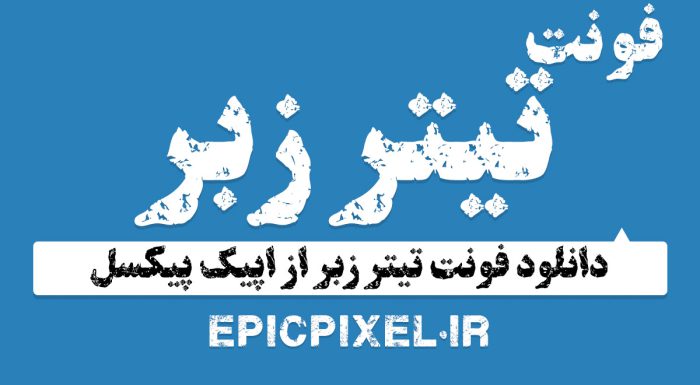
فونت تیتر زبر فارسی
| ⭐ توضیحات | زیر مجموعه از فونت تیتر |
فونت تیتر زبر چگونه از یک فونت ساده یک فونت گرافیکی خلق کنید؟
فکر میکنید برای داشتن یک فونت گرافیکی زیبا و خاص، باید حتما یک طراح حرفهای باشید؟ اگر جوابتان بله است، شاید بعد از خواندن این مقاله نظرتان عوض شود. در این مقاله قصد داریم با شما درباره فونت تیتر زبر صحبت کنیم. یک فونت گرافیکی افکتیو که با تغییر شکل و ایجاد بافت بر فونت تیتر بدست آمده است. این فونت را ملیحه نوازشپور، یک دانشجوی طراحی گرافیک، در قالب یک پروژه دانشجویی خود در کارگاه مسلم ابراهیمی، یک طراح و مدرس فونت، انجام داده است. در این مقاله به شما معرفی میکنیم که فونت تیتر زبر چیست؟ چه ویژگیها و کاربردهایی دارد؟ چگونه میتوانید آن را دانلود و نصب کنید؟ و چگونه از آن در طراحی لوگو و بنر استفاده کنید؟ همچنین نظرات کاربران را درباره این فونت با شما به اشتراک میگذاریم. پس با ما همراه باشید.
فونت تیتر زبر چیست؟
فونت تیتر زبر یک فونت گرافیکی افکتیو است که با تغییر شکل و ایجاد بافت بر فونت تیتر بدست آمده است. فونت تیتر یک فونت ساده و رسمی است که برای نوشتن عناوین و سرصفحات استفاده میشود. این فونت در سال ۱۳۵۰ توسط مسعود کاظمی پور، یک طراح و نقاش، به منظور استفاده در روزنامههای دولتی طراحی شده است. این فونت به دلایل مختلف، مانند خطای ساختار، عدم همخوانی با حروف لاتین، عدم مناسب بودن برای صفحات رنگارنگ و … به مرور کمکاربرد شده است. اما ملیحه نوازشپور، با خلاقانهسازی بر روی این فونت، توانسته است چهره جدید و جذاب به آن ببخشد. این فونت را با استفاده از نقطهزدای دستساز و سپس بازسازی آن در نرمافزار فونت لب (FontLab) خلق کرده است.
ویژگیهای فونت تیتر زبر
فونت تیتر زبر دارای ویژگیهای زیر است:
مدرن و کاربردی: این فونت با داشتن یک ظاهر جدید و متفاوت، میتواند در طراحیهای مدرن و خلاقانه استفاده شود. این فونت با ایجاد تنوع و جذابیت، میتواند نگاه بیننده را به خود جلب کند.
زیبا و خاص: این فونت با داشتن یک بافت گرافیکی زیبا و خاص، میتواند یک حس هنری و زیباییشناسانه به طراحی ببخشد. این فونت با استفاده از نقطهزدای دستساز، یک شخصیت منحصر به فرد به خود پیدا کرده است.
مناسب طراحی لوگو و بنر: این فونت به دلایل مختلف، مناسب برای طراحی لوگو و بنر است. اولا، این فونت با داشتن یک حالت عمودی، میتواند در فضای کم جای بگیرد و به صورت خلاصه و مفید پیام را منتقل کند. دوما، این فونت با داشتن یک حالت گرافیکی، میتواند در تولید تصاویر و نشانههای بصری کمک کند. سوما، این فونت با داشتن یک حالت جذاب، میتواند در جلب توجه بیننده نقش مؤثری داشته باشد.
کاربردهای فونت تیتر زبر
فونت تیتر زبر را میتوانید در موارد زیر استفاده کنید:
طراحی لوگو: اگر میخواهید یک لوگو برای یک برند، یک شرکت، یک سازمان، یک محصول، یک خدمت و … طراحی کنید، میتوانید از فونت تیتر زبر به عنوان نام یا شعار خود استفاده کنید. این فونت با داشتن یک حالت عمودی، گرافیکی و جذاب، میتواند به شما کمک کند تا یک لوگو با شخصیت و حرفهای داشته باشید.
طراحی بنر: اگر میخواهید یک بنر برای یک تبلیغ، یک رویداد، یک پروژه، یک دعوت و … طراحی کنید، میتوانید از فونت تیتر زبر به عنوان عنوان یا پیام خود استفاده کنید. این فونت با داشتن یک حالت عمودی، گرافیکی و جذاب، میتواند به شما کمک کند تا یک بنر با اثربخشی و خلاقانه داشته باشید.
نوشتن مقالات: اگر میخواهید یک مقاله درباره یک موضوع خاص بنویسید، مثلا درباره فونتهای فارسی، میتوانید از فونت تیر زبر به عنوان سرفصلهای مقاله خود استفاده کنید. این فونت با داشتن یک حالت عمودی، گرافیکی و جذاب، میتواند به شما کمک کند تا مقالهای با خوانایی و سئو بالا داشته باشید.
سایر کاربردها: شما محدود به این مثالها نیستید. شما میتوانید از فونت تیتر زبر در هر جایی که خواستید استفاده کنید. مثلا میتوانید از آن در طراحی کارت ویزیت، پوستر، استیکر، تیشرت، لیبل، بروشور، کاتالوگ و … استفاده کنید. همچنین میتوانید از آن در نوشتن دفترچه خاطرات، دعوتنامه، نامه، پیامک و … استفاده کنید. فقط کافی است خلاق باشید و از فونت تیتر زبر به نحو احسن بهره ببرید.